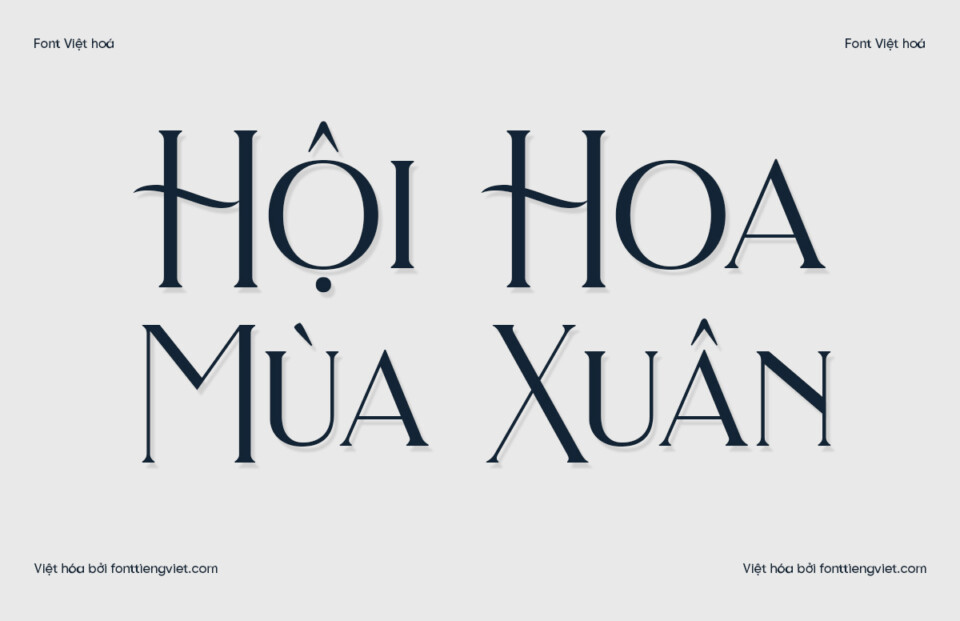
Font Việt hóa 1FTV VIP Brilon
Font Việt hóa 1FTV VIP Brilon – Đỉnh cao nghệ thuật chữ viết sang trọng cho thiết kế chuyên nghiệp
Giới thiệu về Font Việt hóa 1FTV VIP Brilon
Trong thế giới thiết kế đồ họa hiện đại, việc lựa chọn một bộ Font Miễn Phí chất lượng đóng vai trò quyết định đến linh hồn của tác phẩm. Font Việt hóa 1FTV VIP Brilon nổi lên như một biểu tượng của sự thanh lịch, quý phái và đầy tính nghệ thuật. Được lấy cảm hứng từ phong cách Art Deco kinh điển, bộ font này mang đến những đường nét thanh mảnh nhưng vô cùng chắc chắn, giúp các nhà thiết kế dễ dàng truyền tải thông điệp về sự đẳng cấp và tinh tế. Phiên bản Việt hóa bởi 1FTV không chỉ giữ trọn vẹn vẻ đẹp nguyên bản mà còn được tối ưu hóa các dấu câu tiếng Việt một cách tỉ mỉ, giúp văn bản trở nên hài hòa và không bị lỗi hiển thị khi sử dụng trên các phần mềm thiết kế phổ biến hiện nay.
Đặc điểm thiết kế nổi bật của Font Việt hóa 1FTV VIP Brilon
Điểm thu hút nhất của Font Việt hóa 1FTV VIP Brilon chính là sự kết hợp hoàn hảo giữa nét cổ điển và hơi thở đương đại. Các ký tự được tạo hình với độ tương phản cao giữa nét thanh và nét đậm, tạo nên một nhịp điệu thị giác lôi cuốn. Đặc biệt, bộ font này đi kèm với nhiều ký tự thay thế (alternates) và các tính năng OpenType đa dạng, cho phép người dùng tùy biến các đường cong, móc chữ để tạo ra những tiêu đề độc bản. Với phong cách Minimalism sang trọng, Brilon rất phù hợp cho các dự án yêu cầu tính thẩm mỹ cao, nơi mà con chữ không chỉ để đọc mà còn để chiêm ngưỡng như một tác phẩm hội họa thực thụ.
Ứng dụng thực tế của Font Việt hóa 1FTV VIP Brilon trong thiết kế
Nhờ vào diện mạo lộng lẫy, Font Việt hóa 1FTV VIP Brilon thường xuyên được ưu tiên sử dụng trong lĩnh vực thời trang, mỹ phẩm và trang sức cao cấp. Bạn có thể dễ dàng bắt gặp bộ font này trên các bìa tạp chí danh tiếng, các Lookbook thời trang hay bao bì của những thương hiệu xa xỉ. Ngoài ra, Brilon còn là lựa chọn số một cho các ấn phẩm tiệc cưới, từ thiệp mời cho đến bảng tên đón khách, giúp không gian sự kiện thêm phần lãng mạn và cổ điển. Đối với các nhà sáng tạo nội dung trên mạng xã hội, việc sử dụng font chữ này cho các câu trích dẫn (quotes) hoặc ảnh bìa Facebook, Instagram sẽ tạo nên một phong cách cá nhân đậm nét và thu hút sự chú ý của người xem ngay từ cái nhìn đầu tiên.
Lưu ý khi sử dụng Font Việt hóa 1FTV VIP Brilon
Dù sở hữu vẻ đẹp khó cưỡng, nhưng để Font Việt hóa 1FTV VIP Brilon phát huy tối đa hiệu quả, người thiết kế cần biết cách phối hợp màu sắc và khoảng cách chữ (kerning). Do đặc tính là một serif thanh mảnh, Brilon hoạt động tốt nhất ở kích thước lớn làm tiêu đề (Display font) thay vì dùng cho các đoạn văn bản dài (Body text). Hãy ưu tiên đặt font chữ này trên các nền màu đơn sắc hoặc hình ảnh có độ tương phản thấp để các đường nét tinh xảo không bị che lấp. Việc kết hợp Brilon với một font Sans-serif đơn giản sẽ tạo ra sự cân bằng hoàn hảo cho bố cục thiết kế của bạn.